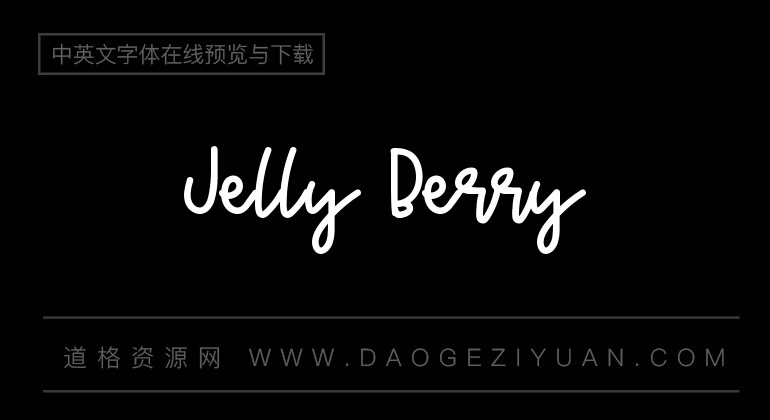
Jelly Berry
? Jelly Berry 是一款超可爱的模型字体,它由著名设计师 Alex Tass 创建。它有着清新的外观,色彩鲜艳,字形优美,而且能够让你的文字显得更加活泼有趣。Jelly Berry 字体采用细节多样的设计,能够让你的文字更加生动,表达更加有趣。它可以用于各种场景,比如标识、广告、海报、插画等,能够让你的文字更加有趣有趣。
Jelly Berry是一款非常不错的手写艺术字体,具有很好的视觉感,适合于文化类的宣传设计、商业类品牌的广告和产品包装设计以及个性化文字排版等较多场景。